艺术字体设计被广泛的应用在视觉识别系统中,具有美观大方,便于阅读和识别等优点。艺术字体设计是在基本字形的基础进行装饰、变化加工而成的。它的特征是在一定程度上摆脱了印刷字体的字形和笔划的约束,根据品牌或企业经营性质的需要进行设计,达到加强文字的精神含义和富于感染力的目的。
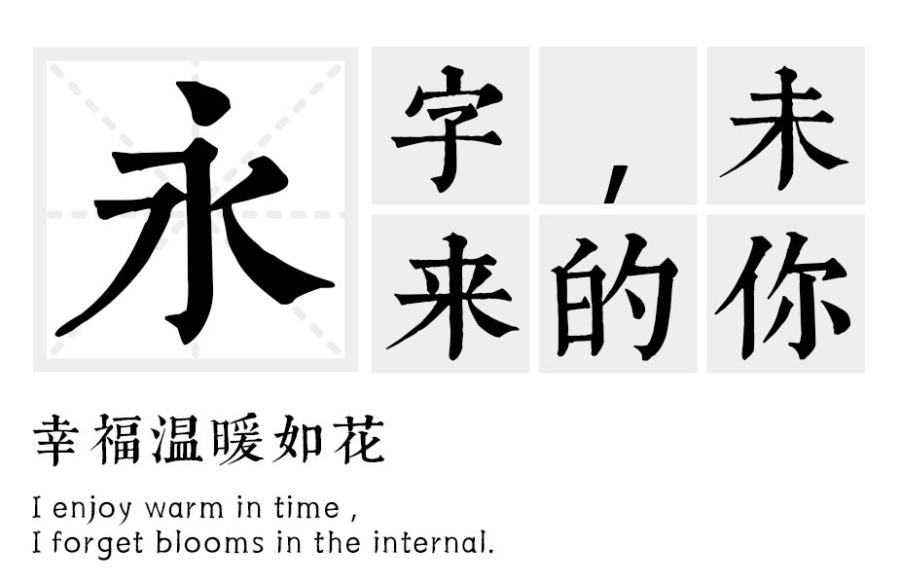
艺术字体设计表达的含意丰富多彩。常用于表现产品属性和企业经营性质,它运用夸张、明暗、增减笔划形象、装饰等手法,以丰富的想象力,重新构成字形,既加强文字的特征,又丰富了标准字体的内涵。同时,在设计过程中,不仅要求单个字形美观,还要使整体风格和谐统一,理念内涵和易读性,以便于信息传播。经过变体设计后的艺术字体,千姿百态,变化万千,是一种字体艺术的创新。